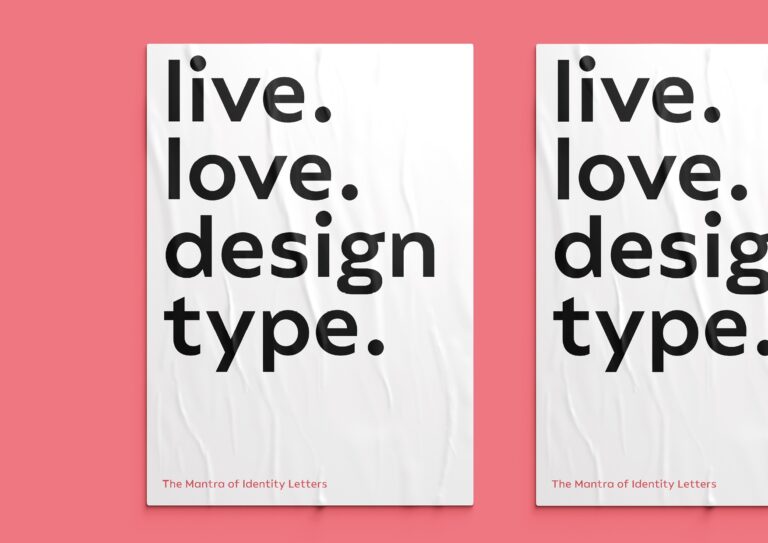
Identity Letters – neue Foundry mit fairem Lizenzmodell
Elf Schriften und ein bewusst einfach gehaltenes Lizenzmodell kennzeichnen die neue Foundry von Moritz Kleinsorge.
»Identity Letters« startet mit einer Bibliothek aus elf akkurat geschnittenen, leistungsfähigen Schriften von Moritz Kleinsorge. Einige davon, etwa die »Allrounder«-Superfamilie, haben wir bereits vorgestellt. Weitere Veröffentlichungen sind in Arbeit.
Der Name Identity Letters ist Programm – im Fokus der neuen Foundry stehen auch Exklusivschriften für starke Unternehmensidentitäten. Kein Wunder: Corporate Typefaces waren schon in der Master-Thesis [corporate-typeface.com] des Designers vom Niederrhein das zentrale Thema.
In Moritz Kleinsorges neuer Foundry Identity Letters wird Schrift kaufen zum Kinderspiel.